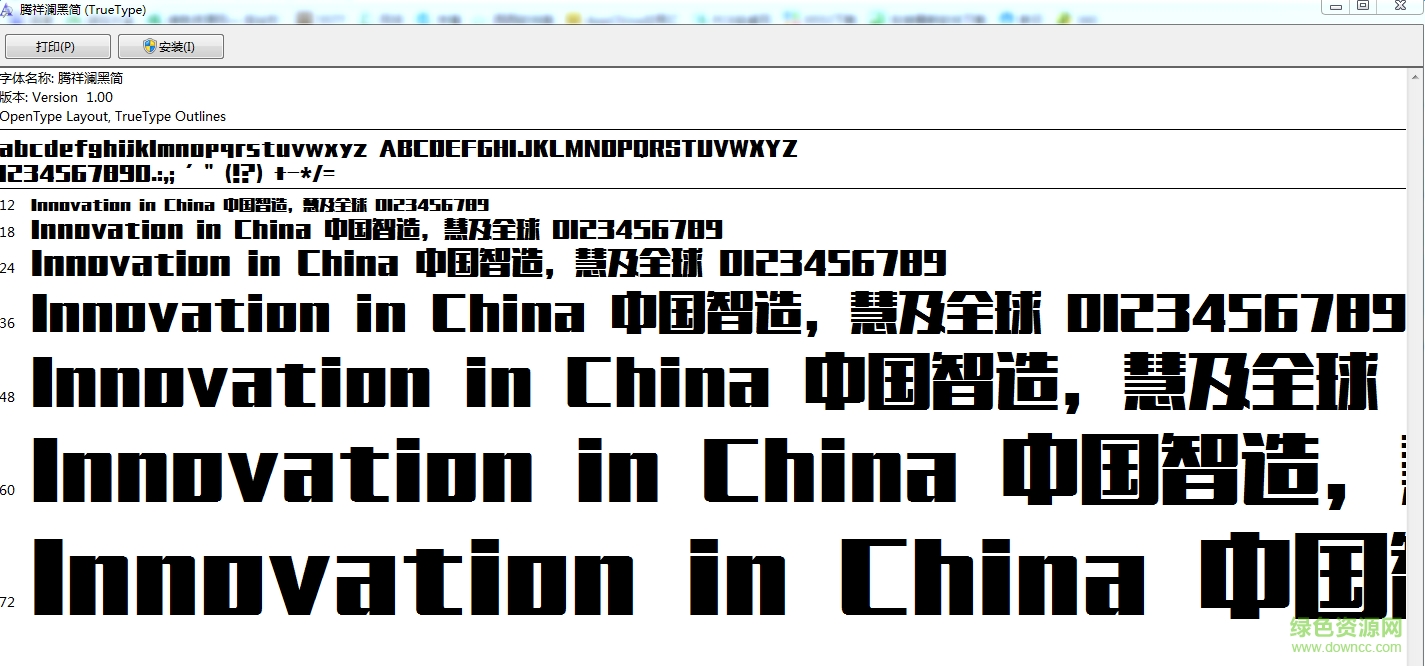
騰祥瀾黑簡字體是一款騰祥類粗體風(fēng)格字體軟件,瀾黑簡字體菱角分明,筆畫錯落有致,整體效果粗壯有力,非常醒目,適用于產(chǎn)品包裝、廣告宣傳等標(biāo)題的應(yīng)用,感興趣的朋友歡迎來綠色資源網(wǎng)下載體驗!
騰祥瀾黑簡字體為騰祥瀾黑字庫是騰祥公司自主精心設(shè)計開發(fā)的一款獨特的美術(shù)黑體字庫。豎筆畫粗壯有力,筆畫間隙恰到好處,字體粗壯醒目,整體排版賦有波瀾壯闊、氣勢磅礴之勢,又蘊含著漢字豐富的內(nèi)涵與力量,故取名瀾黑。